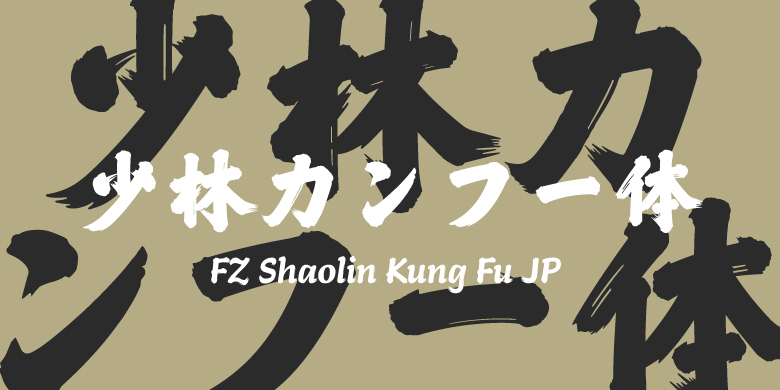
FZ Shaolin Kung Fu JP
字体品牌: 方正字库 设计师:汪文,陈宇,何诗旸 字体分类:书法体 字体属性:外文 字符集:Unicode 发布时间: 2024
方正少林功夫体は、少林寺の「千崖万壑」碑から派生したもので、字体設計では、筆画の主幹部分を滑らかな曲線で設計し、すっきりとしている;筆画の始めと終わりには、毛筆書法の質感を再現し、飛白牽糸のデザイン要素を融合させ、方正少林功夫体が石刻の堅牢な素朴さと同時に毛筆字の細部と感情を持つようにしている。この字体は大気磅礴で、柔らかさと堅牢さを兼ね備え、行書の流れるような美しさと碑文の安定した堅牢さを併せ持ち、少林功夫のイメージと完璧に融合している。方正少林功夫体は多言語の超大字库を計画しており、開発予定言語には、中国語簡体、中国語繁体、BIG5繁体、日本語、韓国語、ラテン語、ギリシャ語、キリル文字、アラビア語などが含まれている。異なる言語の文字には異なる書き方と美的伝統があり、デザインでは各言語の特性を考慮しつつ、全体のスタイルの統一性を保っている。
デザイナー:汪文、陳宇、何诗旸(欧文・多言語)
字体ブランド:方正字庫
デザイナー:汪文,陳宇,何诗旸
字体分類:常規書写・毛筆